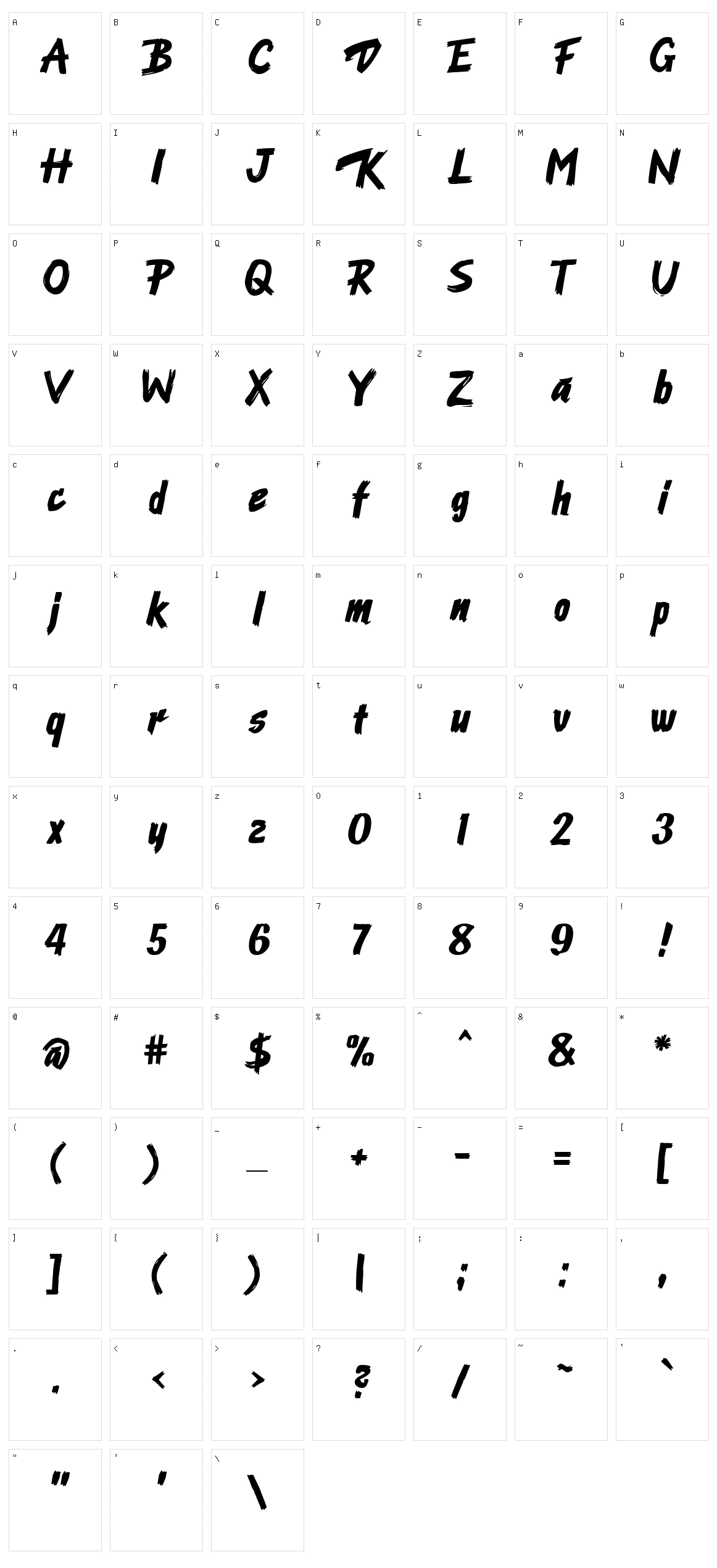
Diese Schriftart geht zurück auf die Titelgrafik der deutschen Krimiserie âDer Kommissarâ, die das ZDF 1969-1976 in fast hundert Folgen ausstrahlte.
Die Titelgrafik (u.a. auf Wikipedia abrufbar) ist handgeschrieben mit schnellen, fetten Pinselstrichen, wie an den doppelt vorkommenden Buchstaben m, s und r leicht erkennbar ist. Sie wurden digitalisiert, und aus diesem Material konnte auch fast der gesamte Bestand der Kleinbuchstaben entwickelt werden. Für die GroÃbuchstaben und Ziffern fanden sich andere Vorbilder, die dem Charakter der Schrift angepasst wurden.
Der Buchstabenbestand deckt unter anderem die Sprachen Deutsch, Englisch, Französisch, Spanich, Italienisch, Portugiesisch, Dänisch, Schwedisch, Norwegisch, Isländisch und Türkisch ab.
In Anspielung auf den Hauptdarsteller Erik Ode ("der" Kommissar Herbert Keller) erhielt die Schrift ihren Namen.
This typeface originates in the Title graphics of the German TV police series "Der Kommissar" (The Police Commissioner) broadcast in 1969 to 1976.
The graphic title consists of fast, bold brush strokes and was hand-made. The letters were scanned and digitized, and from that material almost all of the lowercase characters could be derived. Uppercase and figures took inspiration from other sources which were adapted to fit the general character of the typeface.
The font works with many (mainly West-)European languages, such as English, German, French, Spanish, Italian, Portuguese, Danish, Swedish, Norwegian, Islandic and Turkish.
The name of the font alludes to the actor who played the main charakter, Erik Ode. In English it means "Ode to Erik".